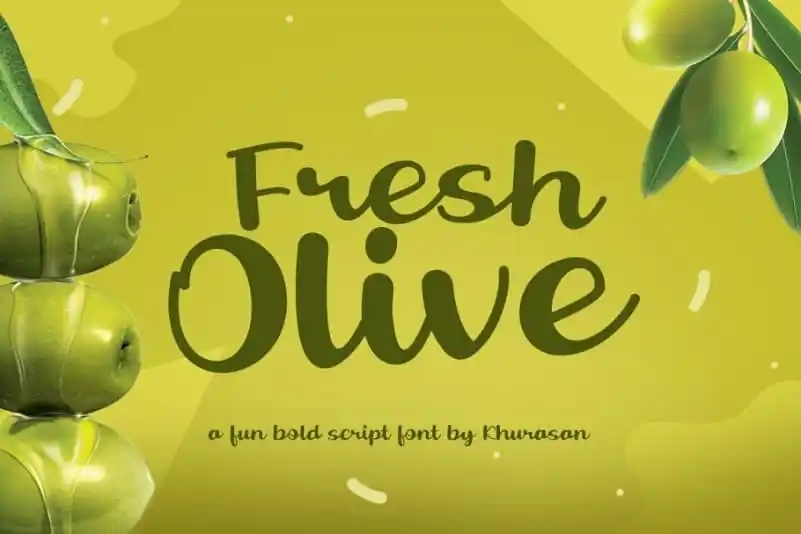
Fresh Olive Script Font – Download Grátis
A Fresh Olive Script Font é uma opção elegante para projetos que buscam um toque alegre e envolvente. Sua tipografia script foi criada pelo designer khurasan, especializada em apresentar um tom de amêndoas frescas e suaves, perfeitamente adequada para designs infantis ou relacionados à família, como cartões de aniversário, logotipos e cartazes. A fonte é uma excelente escolha se você está buscando algo alegre e versátil, pronta para qualquer tipo de projeto gráfico, desde o desenvolvimento de um novo logo até a criação de um site atraente ou uma publicação impressa. Além disso, a Fresh Olive Script Font suporta múltiplas línguas, tornando-a ainda mais versátil e adaptável para diferentes contextos culturais. Seja em um projeto para sua empresa ou uma criação original que expressa seu estilo único, esta fonte é perfeita para manter o design alegre e vibrante sempre em alta.